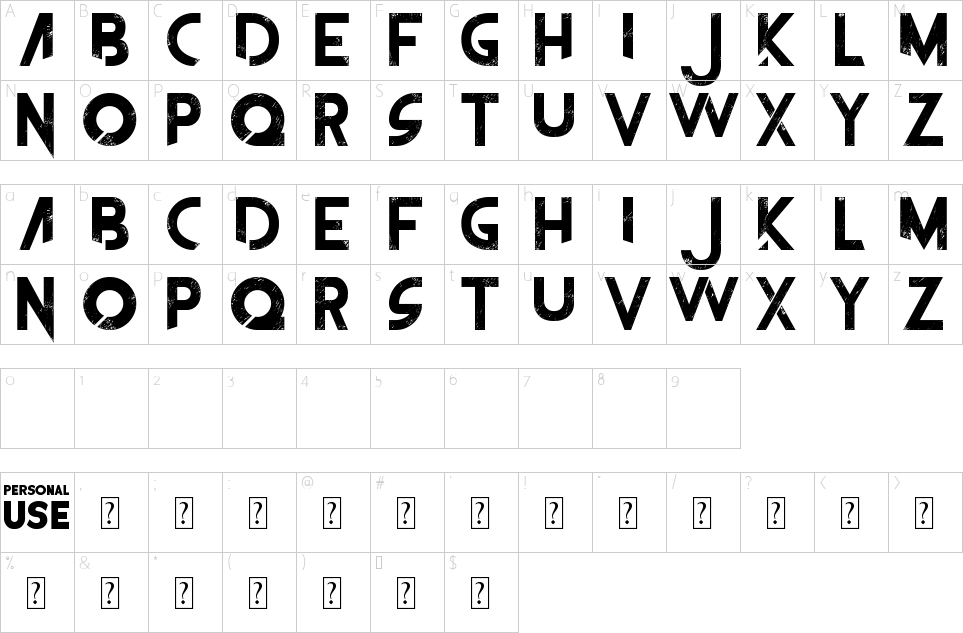
The FrontMan Font – Fonte Grátis
The FrontMan Font
A fonte The FrontMan é uma escolha ótima para qualquer designer que procura uma fonte de negócios moderna e atraente. Desenvolvida pela LJ Design Studios, The FrontMan traz uma elegância sóbria que combina bem em qualquer projeto. Esta fonte gratuita é perfeita tanto para os usuários do Windows quanto para aqueles que preferem o Mac. Com um design minimalista e uma forte identidade visual, The FrontMan se destaca como uma opção confiável para qualquer projeto onde você precisa de uma fonte forte e legível. Embora não tenha sido criada especificamente para usar em aplicativos de negócios, The FrontMan é uma escolha inteligente para qualquer projeto onde você precisa de uma fonte que transmita confiabilidade e seriedade. Se você está procurando por um estilo moderno e de negócios, The FrontMan é uma fonte imperdível para incluir em seu arsenal de recursos gráficos.